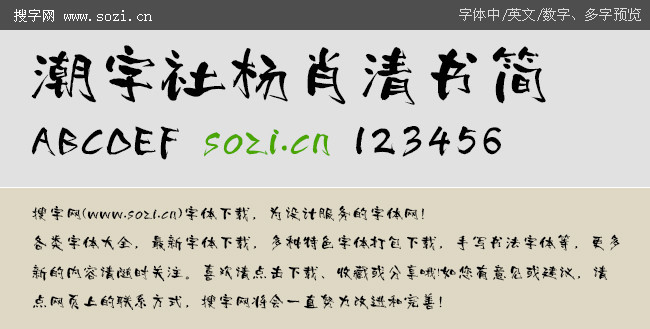
潮字社楊肖清書簡
搜字網(wǎng)提供一款潮字社楊肖清書簡中文字體下載,潮字社楊肖清書字體是由銳字工房開發(fā)設(shè)計的一款中文手寫字體,該字體筆觸粗細(xì)適中,整個字體非常流暢自然,大氣中還帶一些時尚,適用于書籍封面設(shè)計、報刊標(biāo)頭設(shè)計,包裝設(shè)計,海報設(shè)計等廣告應(yīng)用。(此款為個人非商用版,如需商用請聯(lián)系銳字工房購買)